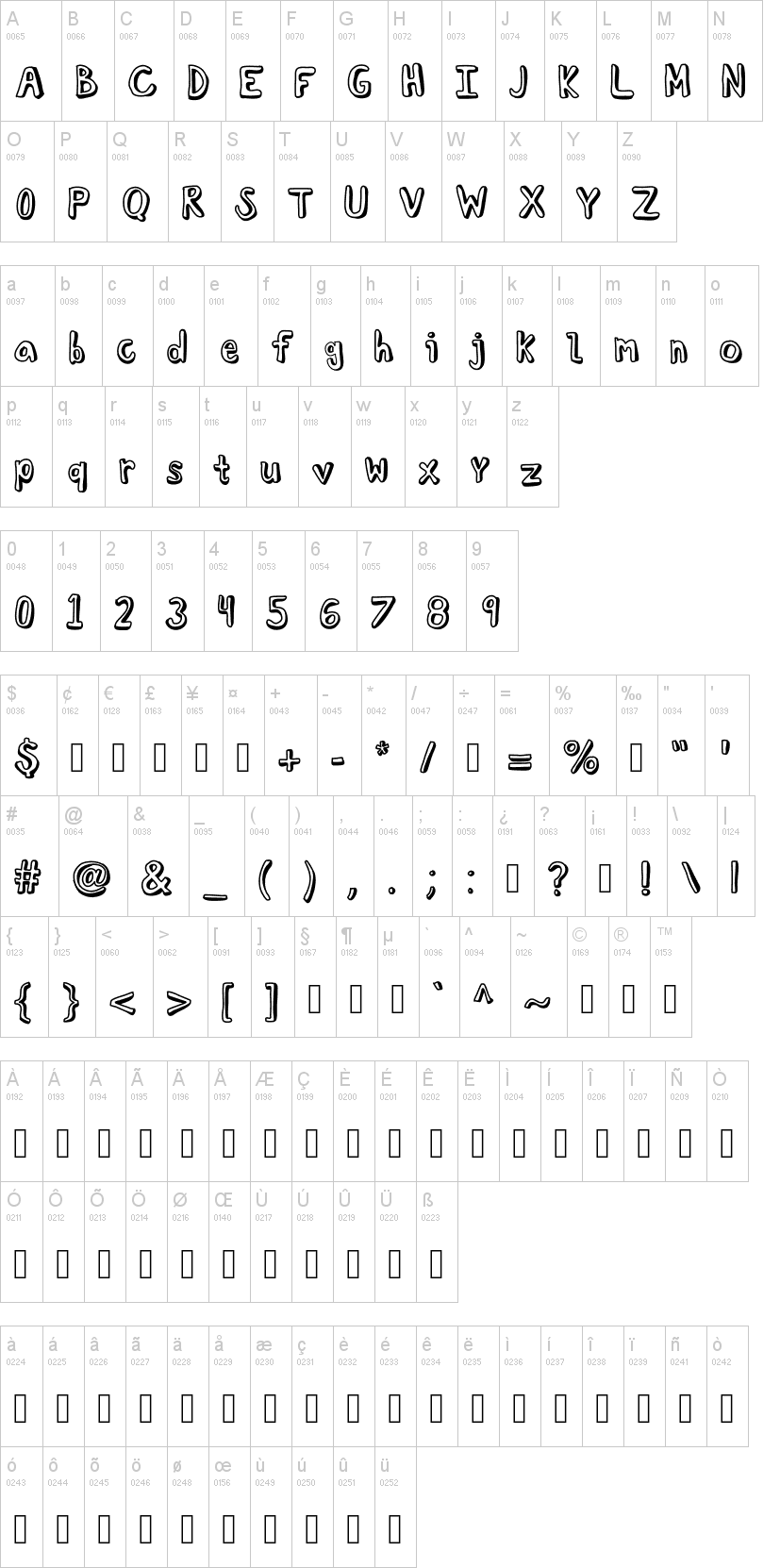
KB Troubled Soul
KB Troubled Soul 是一款由Konstantine Studio设计的手写体字体,具有独特的复古风格。它的设计灵感来自20世纪60年代的流行文化,具有细腻的笔触,让人感受到温暖的气息。它的字体特点为:粗犷的线条,活泼的节奏,清晰的笔画,柔和的曲线,以及自然的节奏感。该字体具有极强的视觉冲击力,适合用于海报、标志、标题、封面等设计项目。
KB Troubled Soul是一款非常不错的手写艺术字体,具有很好的视觉感,适合于文化类的宣传设计、商业类品牌的广告和产品包装设计以及个性化文字排版等较多场景。